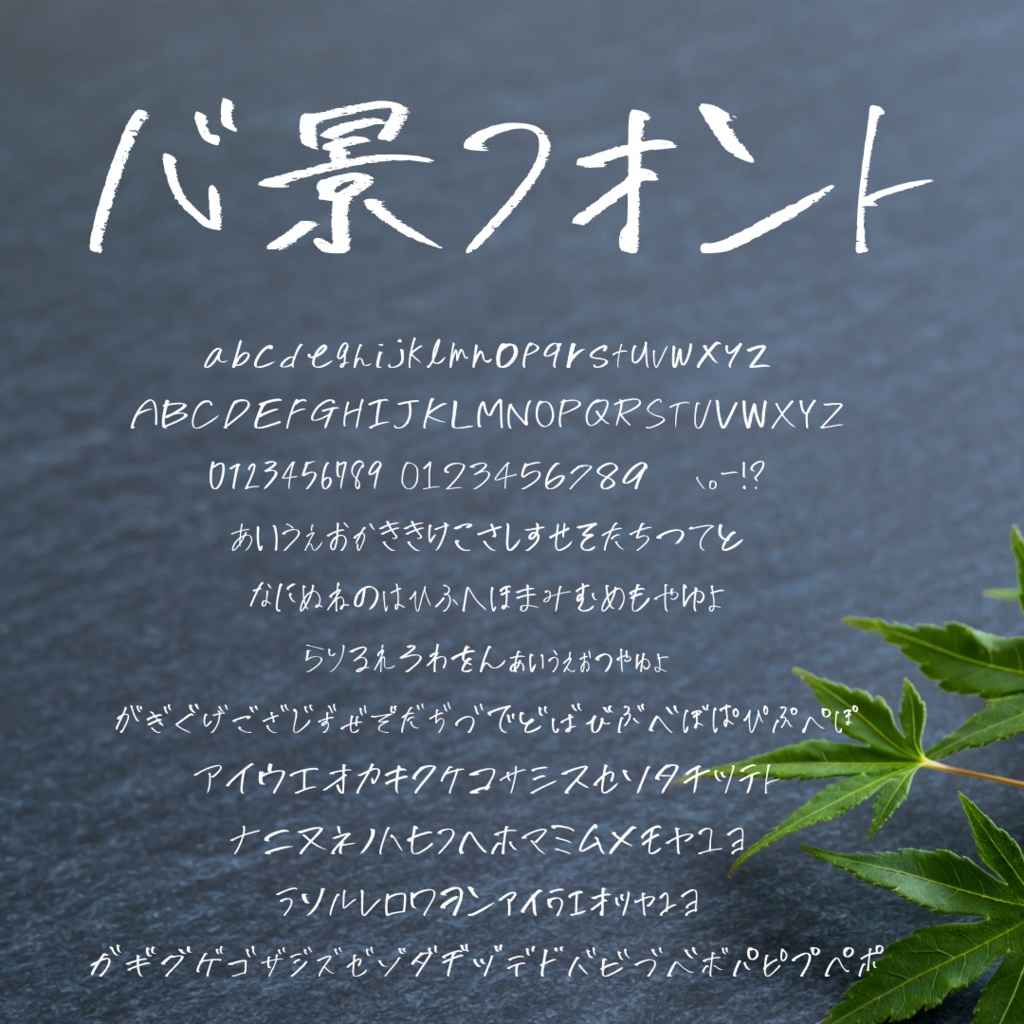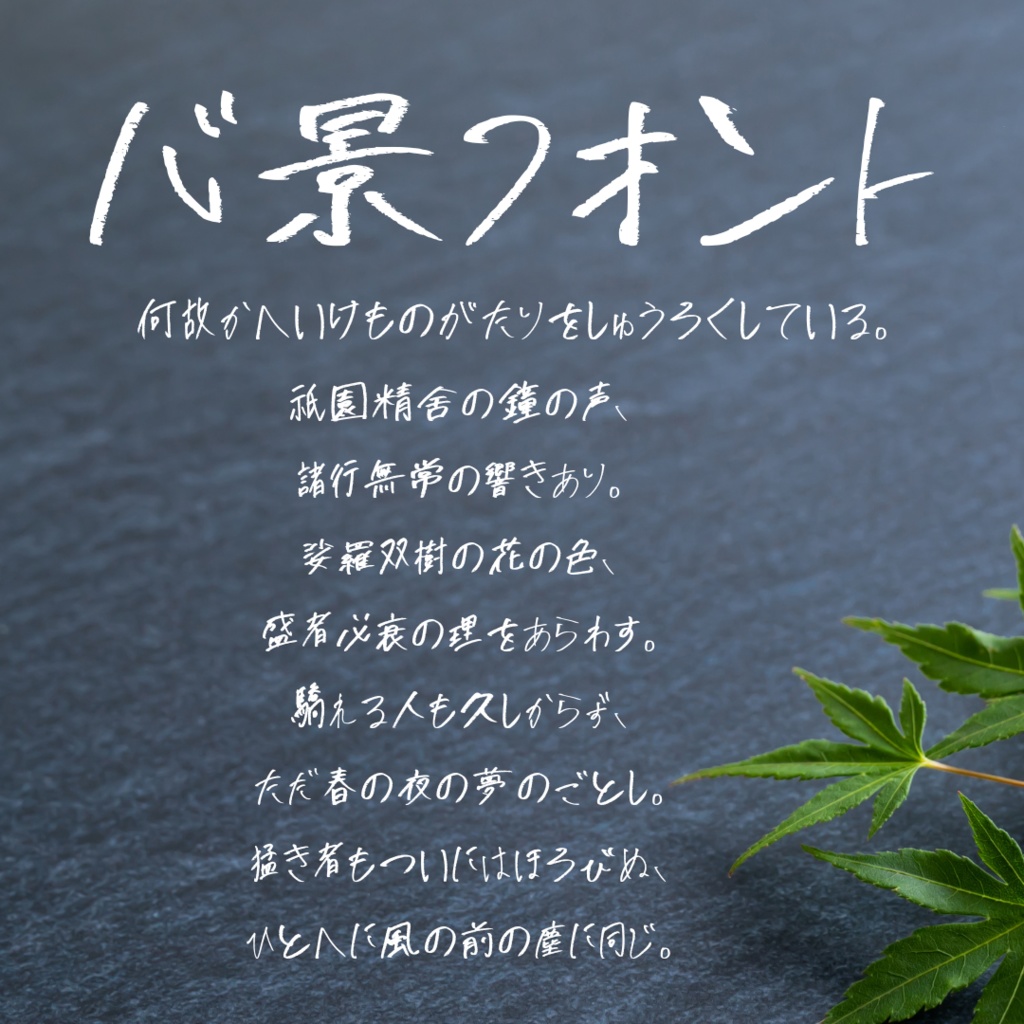
心景フォントボールドβ版
心景フォント β版 あなたの情景に、ひと文字のぬくもりを。 写真に添えることば、ZINEのタイトル、推し活の手紙や創作に—— 誰かの心の風景を、そっと編むような手書き文字を目指しました。 ⸻ 【収録内容】 • ひらがな(46字+濁音・拗音など) • カタカナ(46字+濁音・拗音など) • 英数字(A~Z、a~z、0~9) • 記号(。、!?など) • 一部漢字(平家物語冒頭) 推奨使用サイズ:50pt以上 太字は未対応。細め〜中細の自然な手書き線です。 ⸻ 【同梱物】 • フォントファイル(OTF) • サンプル画像(png) • readme(テキスト) ⸻ 【商用利用について】 以下いずれかのSNSアカウントをフォローいただくことで、商用利用が可能です。 • Instagram @shinkei_letters ⸻ 【ご注意】 • フォントデータの再配布・販売は禁止です。 • 本フォントを使用したロゴの商標登録は不可です。 • 制作中のベータ版につき、今後アップデートを予定しています。 ⸻ 「文字を編むように、想いを綴る。」 心景フォントが、あなたの心の風景に寄り添えますように。